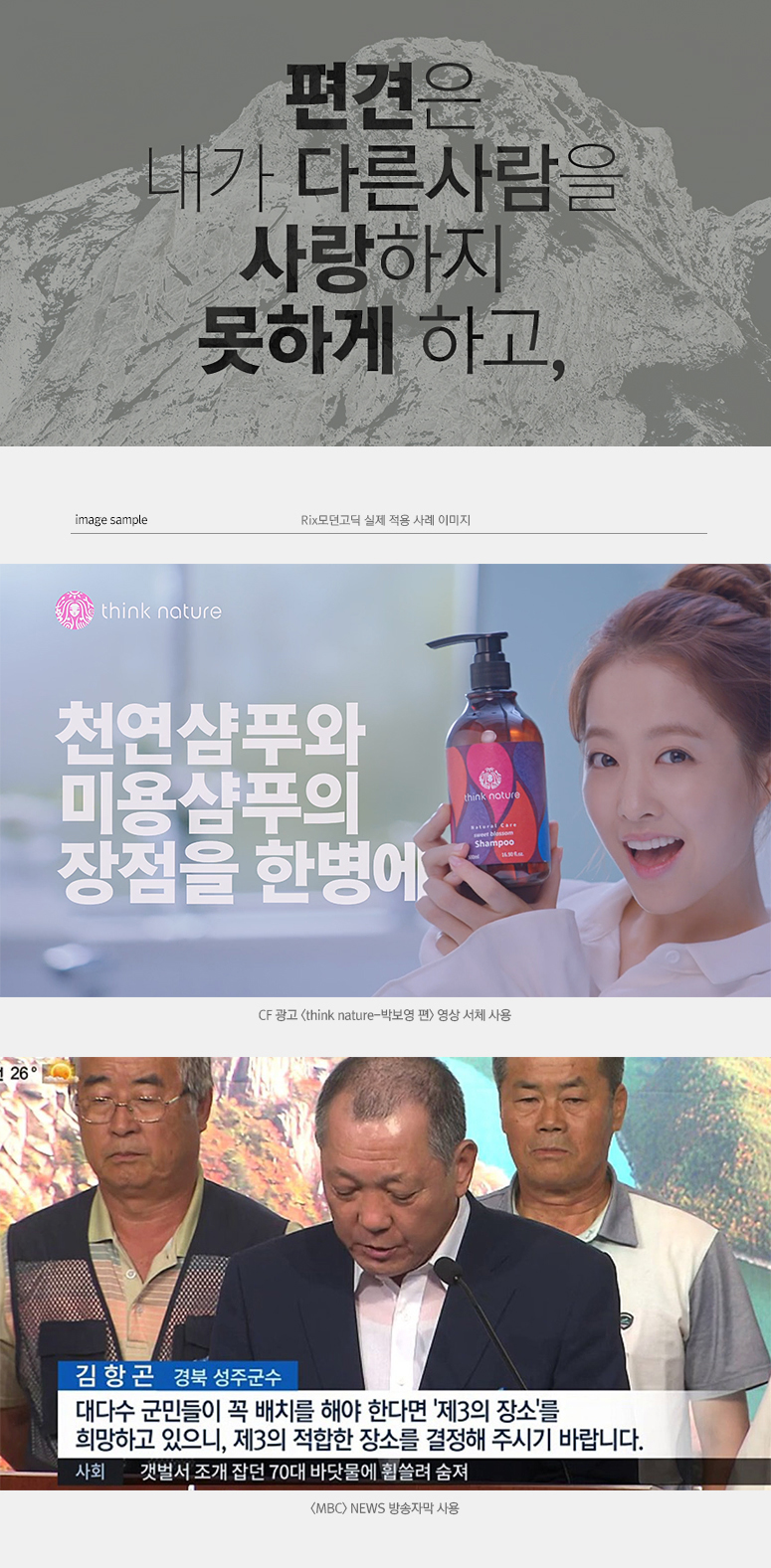
Rix모던고딕은 디자인과 실용성을 갖춘 현대적인 고딕 폰트입니다.
현대적이고 도회적인 본문형의 서체로 적정 자간과 장평의 설정으로 편집자의 수정 없이 최고의 편집 효과를 낼 수 있습니다. 획의 양 끝에 적용된 미세한 세리프로 화면에서 모서리 부분이 뭉개지는 느낌을 없애고 힘 있고 세련된 느낌을 만들어 냅니다.